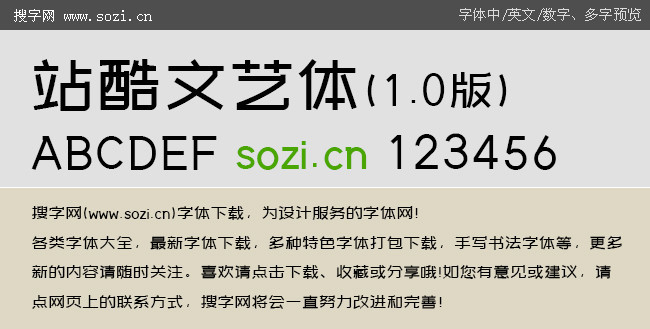
站酷文藝體1.0
搜字網(wǎng)提供一款站酷文藝體1.0中文字體下載,站酷文藝體是一款,由劉兵克工作室團(tuán)隊(duì)、以及劉兵克字體設(shè)計(jì)直播課的近50位學(xué)員共同創(chuàng)作完成,結(jié)構(gòu)上選用了略扁的形態(tài),其筆畫粗細(xì)基本保持一致,字形新穎獨(dú)特,簡潔有力,清新淡雅,文藝范十足。本字庫供全渠道免費(fèi)個(gè)人使用和商業(yè)用途,適用于書籍排版、報(bào)紙排版、畫冊(cè)設(shè)計(jì),網(wǎng)頁設(shè)計(jì)等應(yīng)用。